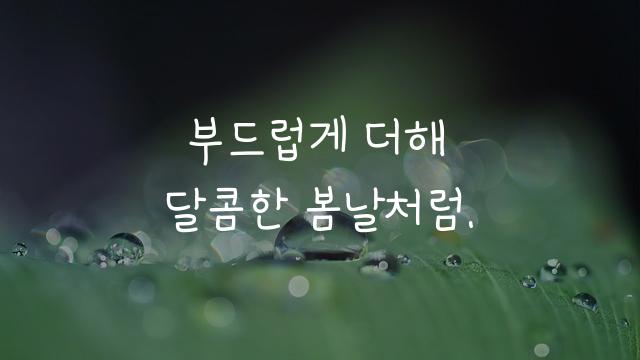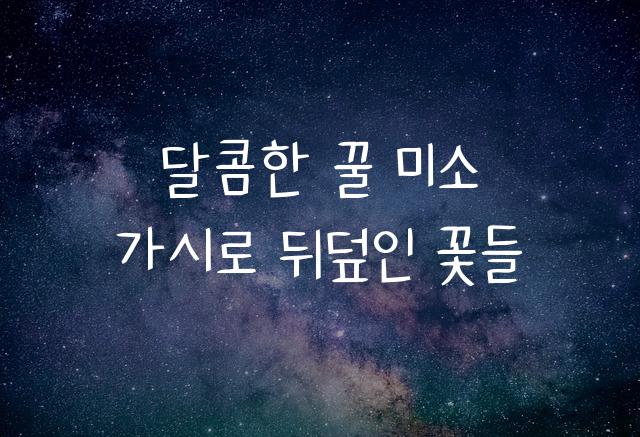
둘기마요고딕은 또박또박한 손글씨 스타일의 귀여운 고딕 폰트로, 따뜻한 감성을 전달하며 독자의 시선을 사로잡습니다. 이 폰트는 친근감을 주며 텍스트를 읽는 즐거움을 더합니다.
둘기마요고딕은(는)
기본 고딕, 손글씨, 귀여운 스타일, 감성적인 계열의 생김새를 가지고 있으며
어린이 책, 디지털 광고, 소셜 미디어 등에서 자주 활용되며, 효과적인 메시지 전달에 적합합니다.
이 폰트는 라이프스타일, 소매/유통, 유아/가족 분야에 잘 어울리며,
귀여운, 창의적인, 재미있는 느낌을 담고 있는 것이 특징입니다.